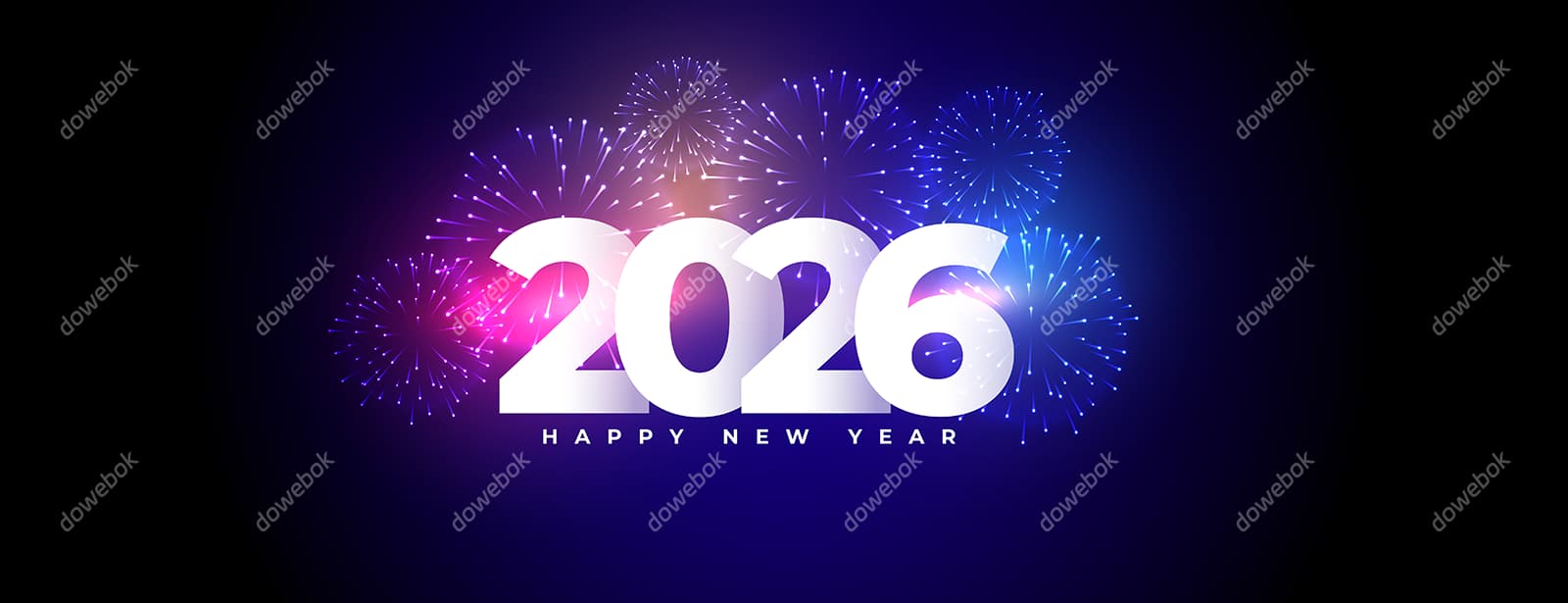
这是一款由炫彩烟花设计的 2026 新年快乐 banner 矢量素材,深暗背景上,炫彩烟花绽放成渐变光影,衬托着醒目的白色 “2026” 字体,下方配 “Happy New Year” 英文。烟花的紫蓝粉渐变营造出热烈的跨年氛围,白字与暗底的对比让主题清晰突出,整体设计既显庆典的动感绚烂,又以简洁排版传递出新年的欢快张力,适配跨年海报、电子祝福素材。